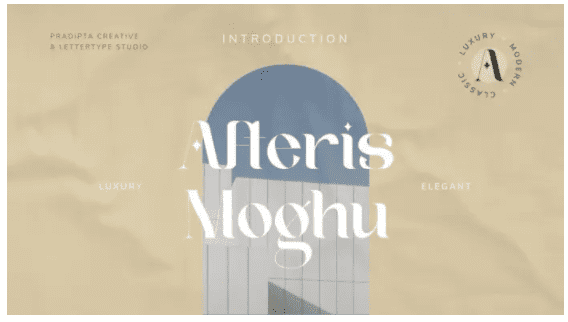
Название: Afteris Moghu Font (2021)
Afteris Moghu Serif - это современный, классический или винтажный шрифт.
Этот шрифт идеально подойдет для дизайна логотипов, брендинга, одежды, вывесок, плакатов, свадебных приглашений и многого другого! Моей целью при создании этого шрифта было создание смеси шрифтов с засечками в современном и классическом стилях, что поможет вашему проекту быть более совершенным и красивым. Не пропустите!
Название: Afteris Moghu Font (2021)
Afteris Moghu Serif - это современный, классический или винтажный шрифт.
Этот шрифт идеально подойдет для дизайна логотипов, брендинга, одежды, вывесок, плакатов, свадебных приглашений и многого другого! Моей целью при создании этого шрифта было создание смеси шрифтов с засечками в современном и классическом стилях, что поможет вашему проекту быть более совершенным и красивым. Не пропустите!